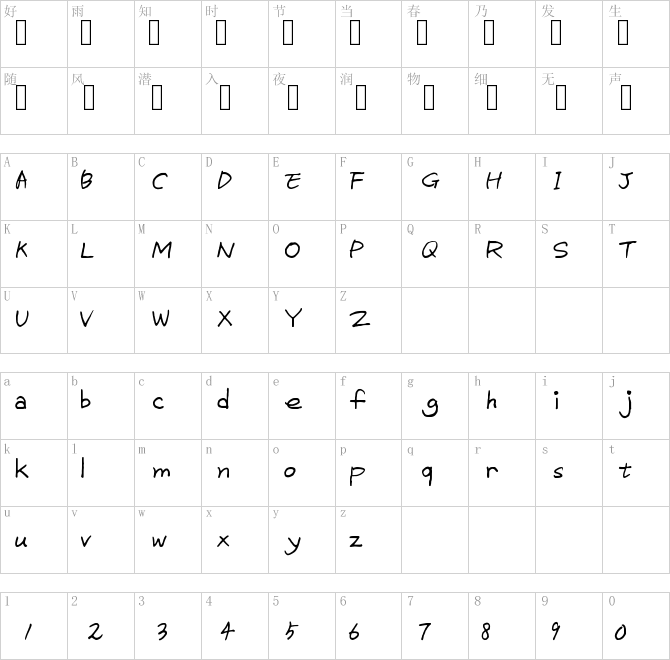
나눔손글씨 강부장님체韩国字体
나눔손글씨 강부장님체韩国字体,这款字体结构工整、笔画清晰,兼顾美观与易读性,适用于标题、正文、海报、包装、LOGO 等多种场景。字形优雅稳定,风格百搭耐看,适配日常排版与创意设计,让文字呈现更舒适、更具质感。나눔손글씨 강부장님체韩国字体一笔一画,皆是细节,以均衡的比例、流畅的线条打造舒适视觉体验,字形端正大气,风格简约现代。无论是商业设计、品牌宣传还是日常排版,都能轻松驾驭,让文字更有格调与力量。나눔손글씨 강부장님체韩国字体字体下载。